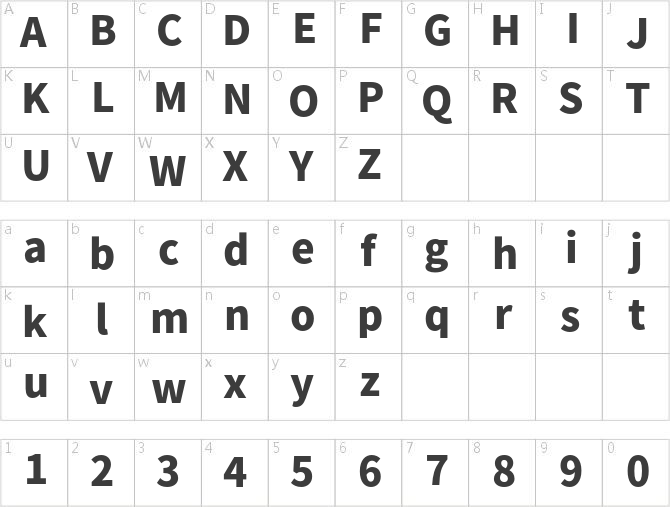
SourceHanSans-Heavy 詳情頁
思源
SourceHanSans-Heavy字體字庫是一款讓人賞心悅目、百看不厭的英文字體,適合各類廣告和產(chǎn)品包裝設(shè)計(jì)應(yīng)用,字體大小16.59MB,格式為otf字體,上傳用戶是82年的拉菲,作者/版權(quán)方為未知